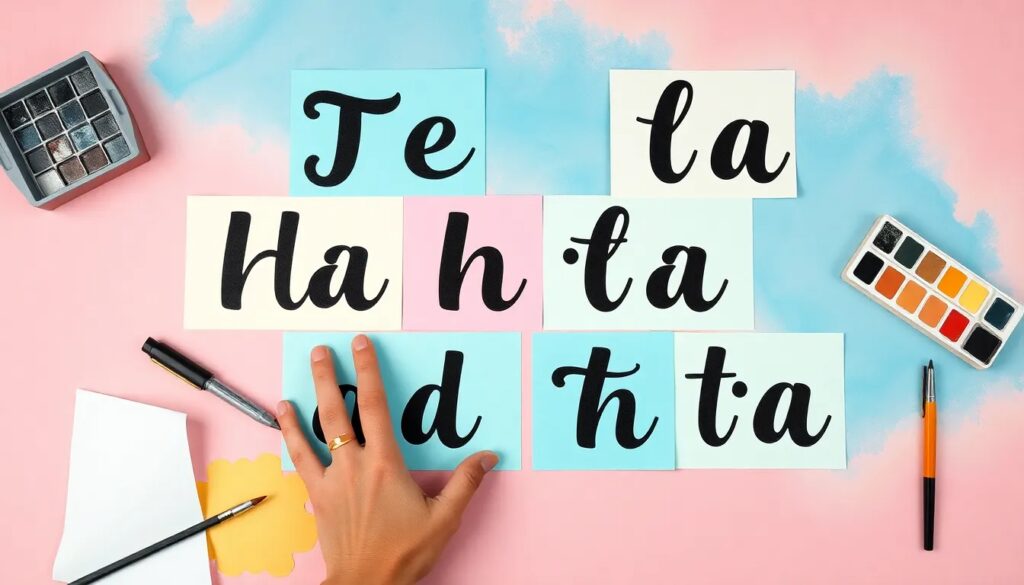
Tipografía letras Instagram: las mejores fuentes para tus publicaciones
Las tipografías y letras en Instagram juegan un papel crucial en cómo los usuarios perciben tu contenido. Utilizar fuentes atractivas puede hacer que tus publicaciones se destaquen entre la multitud y reflejen tu personalidad o la de tu marca. Con una variedad de estilos disponibles, puedes mejorar la estética de tu perfil y atraer más seguidores.
Con el auge de las redes sociales, especialmente Instagram, saber elegir la tipografía adecuada se ha vuelto esencial. Este artículo te guiará a través de los diferentes tipos de letras, herramientas disponibles y consejos para crear un perfil atractivo que capte la atención de tus seguidores.
¿Qué son las letras para Instagram?
Las letras para Instagram son estilos tipográficos que puedes utilizar para mejorar la apariencia de tus publicaciones y historias. Estas fuentes personalizadas pueden transformar un texto ordinario en uno visualmente atractivo. Existen diferentes aplicaciones y herramientas que permiten a los usuarios crear y copiar estas letras fácilmente.
Además, los usuarios pueden mezclar letras con emojis y símbolos, añadiendo un toque único a sus publicaciones. La tipografía juega un papel importante en la comunicación visual, y elegir la correcta puede influir en cómo tu mensaje es recibido.
Por otro lado, hay una amplia gama de fuentes disponibles, desde las más clásicas hasta las más modernas y decorativas. Explorar estos estilos puede ayudarte a encontrar la tipografía ideal que se adapte a tu contenido.
¿Cómo funciona el conversor de letras para Instagram?
El conversor de letras para Instagram es una herramienta que transforma tu texto en diferentes estilos tipográficos. Funciona mediante una interfaz sencilla, donde introduces el texto que deseas cambiar y seleccionas el estilo que prefieres. Al final, puedes copiar y pegar el resultado en tu publicación o biografía.
Entre las herramientas más populares se encuentra Glyphy, que ofrece una variedad de estilos para elegir. Este tipo de conversores son gratuitos y fáciles de usar, lo que los convierte en una opción ideal para quienes buscan modernizar su contenido.
Adicionalmente, muchos de estos conversores utilizan el sistema Unicode, permitiendo que las letras se visualicen correctamente en Instagram y otras plataformas. Esto asegura que tu texto no solo se vea bien, sino que también sea legible en diferentes dispositivos.
¿Cuáles son los tipos de letras más usadas en Instagram?
Las tipografías más populares en Instagram incluyen una amplia variedad de estilos que se adaptan a diferentes gustos y propósitos. Algunos de los estilos más utilizados son:
- Fuentes cursivas: Muy utilizadas para dar un toque personal y elegante.
- Fuentes de estilo gótico: Perfectas para un look dramático y atractivo.
- Fuentes modernas: Limpias y minimalistas, ideales para marcas contemporáneas.
- Fuentes decorativas: Para darle un carácter juguetón a tus publicaciones.
- Fuentes con sombras: Añaden profundidad y un aire tridimensional al texto.
Cada tipo de letra puede evocar diferentes emociones y reacciones en tu audiencia. Por lo tanto, es importante elegir una tipografía que refleje la identidad de tu marca y el mensaje que deseas transmitir.
Además de estas opciones, la combinación de diferentes fuentes puede crear un efecto visual atractivo en tus publicaciones. Experimentar con estas combinaciones puede ayudarte a encontrar un estilo único que se destaque.
¿Para qué sirven las fuentes de Instagram?
Las fuentes de Instagram sirven para varios propósitos clave que pueden mejorar significativamente la experiencia del usuario. En primer lugar, ayudan a diferenciar tu contenido del de otros usuarios, dándote una ventaja competitiva. Esto es especialmente importante en plataformas saturadas como Instagram.
Además, las tipografías pueden comunicar la personalidad de tu marca. Por ejemplo, si tienes un negocio de moda, usar fuentes elegantes puede resonar mejor con tu audiencia. Por otro lado, si tu contenido es más divertido o desenfadado, fuentes decorativas pueden ser más adecuadas.
Las fuentes también son una excelente manera de atraer la atención de tus seguidores. Un texto llamativo puede hacer que más personas interactúen con tu publicación, ya sea a través de "me gusta", comentarios o compartidos. En resumen, las fuentes son una herramienta clave para el engagement en Instagram.
¿Cómo crear letras bonitas para Instagram?
Crear letras bonitas para Instagram no tiene por qué ser complicado. Aquí tienes algunos consejos que te ayudarán a destacar tus publicaciones:
- Utiliza herramientas en línea como Glyphy o Generador de Letras para Instagram. Estas plataformas te ofrecen distintos estilos para personalizar tus textos.
- Combina fuentes con emojis. Esta mezcla puede hacer que tu perfil sea más dinámico y atractivo.
- Experimenta con el tamaño y el color del texto. A veces, un simple cambio en el color puede marcar una gran diferencia.
- Usa espacios y saltos de línea estratégicamente para que tu texto sea más legible y visualmente agradable.
- Incorpora símbolos y caracteres especiales. Esto puede añadir un efecto visual único a tu contenido.
No tengas miedo de ser creativo. A menudo, las publicaciones más originales son las que capturan la atención del público. Recuerda que la coherencia visual en tu feed también es importante para mantener la identidad de tu marca.
¿Qué aplicaciones pueden cambiar la letra en Instagram?
Existen múltiples aplicaciones que pueden ayudarte a cambiar la letra en Instagram de manera efectiva. Algunas de las más populares incluyen:
- Glyphy: Como se mencionó anteriormente, es una herramienta que permite crear estilos tipográficos únicos fácilmente.
- Fonts: Esta aplicación ofrece una variedad de fuentes que puedes usar en distintas redes sociales.
- Stylish Text: Permite personalizar el texto y copiarlo directamente en Instagram.
- Cool Fonts: Proporciona una amplia gama de estilos para elegir y es muy fácil de usar.
- Fancy Text: Esta app convierte tu texto en diferentes estilos y te permite copiarlo y pegarlo donde desees.
Estas aplicaciones son muy útiles para quienes desean añadir un toque especial a sus publicaciones. Usarlas puede mejorar la estética de tu perfil y atraer más interacciones.
¿Por qué usar un conversor de fuentes?
Usar un conversor de fuentes puede facilitar significativamente la creación de contenido atractivo en Instagram. Las principales razones para hacerlo incluyen:
1. Diversidad de estilos: Un conversor te ofrece una variedad de tipografías que pueden adaptarse a diferentes temáticas y propósitos.
2. Facilidad de uso: Estas herramientas suelen ser intuitivas y rápidas, permitiendo cambios en segundos.
3. Compatibilidad Unicode: Aseguran que tus letras se visualicen correctamente en diferentes dispositivos y sistemas operativos.
4. Personalización: Puedes crear un estilo único que se alinee con la identidad de tu marca o tu personalidad.
Sin duda, utilizar un conversor de fuentes es una excelente manera de mejorar tu contenido y atraer a más seguidores en Instagram.
Preguntas frecuentes sobre las letras para Instagram
¿Cuál es la fuente de la letra de Instagram?
La fuente utilizada por Instagram en su logotipo es una variante personalizada de la tipografía "Billabong". Sin embargo, para publicaciones, los usuarios pueden elegir entre una variedad de fuentes disponibles a través de herramientas y aplicaciones de conversión. Utilizando estas herramientas, puedes replicar el estilo o elegir fuentes que se alineen con el diseño que deseas para tu contenido.
¿Cómo poner estilo de letra en Instagram?
Para poner estilo de letra en Instagram, puedes utilizar aplicaciones y sitios web que ofrecen conversores de texto. Simplemente escribe el texto que deseas modificar, elige el estilo que te guste y copia el resultado. Luego, pega el texto en tu publicación, historia o biografía. Recuerda que la clave es experimentar con diferentes estilos hasta encontrar el que mejor se adapte a tu contenido.
¿Cómo puedo cambiar la fuente de las letras en Instagram?
Cambiar la fuente de las letras en Instagram es fácil. Utiliza un conversor de letras en línea, introduce el texto que quieres cambiar y selecciona el estilo que prefieras. Después, solo copia y pega el texto en tu publicación o biografía de Instagram. Este proceso es rápido y te permite agregar un toque personal a tus mensajes.
¿Cuál es la mejor letra para Instagram?
La "mejor" letra para Instagram varía según el estilo personal y la temática del contenido. Sin embargo, algunas fuentes populares incluyen las cursivas para un toque elegante y las fuentes modernas para un aspecto limpio. Lo más importante es que la tipografía elegida refleje tu personalidad o la de tu marca, y que sea legible para tus seguidores.